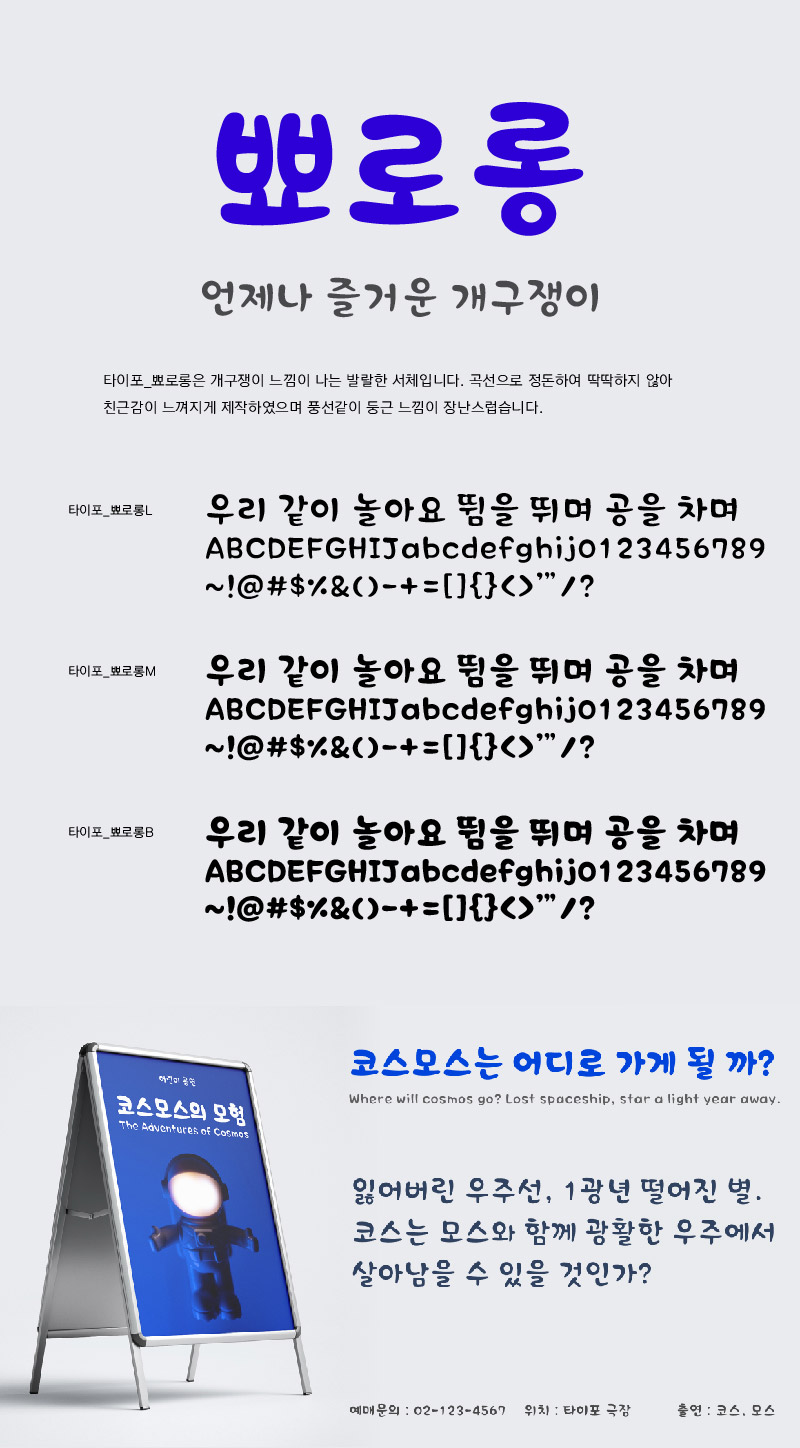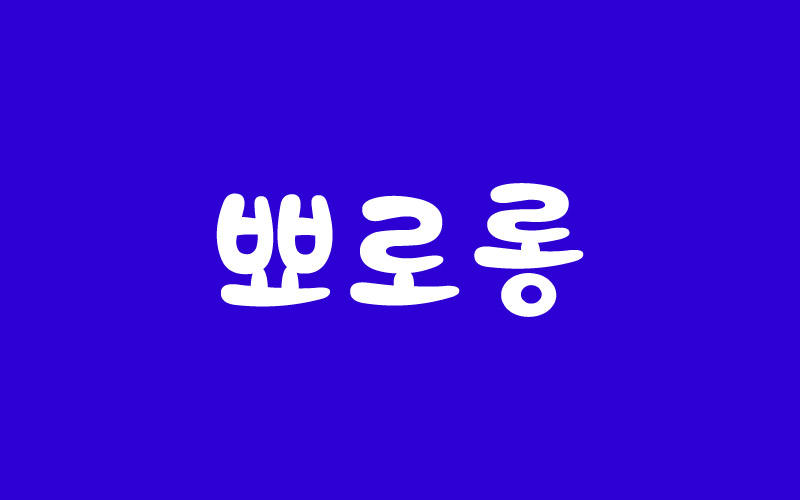
타이포_뾰로롱
3 종 - Bold, Medium, Light개구쟁이 느낌이 나는 발랄한 서체입니다. 곡선으로 정돈하여 딱딱하지 않아 친근감이 느껴지게 제작하였으며 풍선같이 둥근 느낌이 장난스럽습니다.
| 폰트명 | 타이포_뾰로롱 / Typo_Ppyororong |
|---|---|
| 폰트디자인 | 임진욱/한효영 |
| 디자인디렉팅 | 임진욱 |
| 출시년도 | 2009년 |